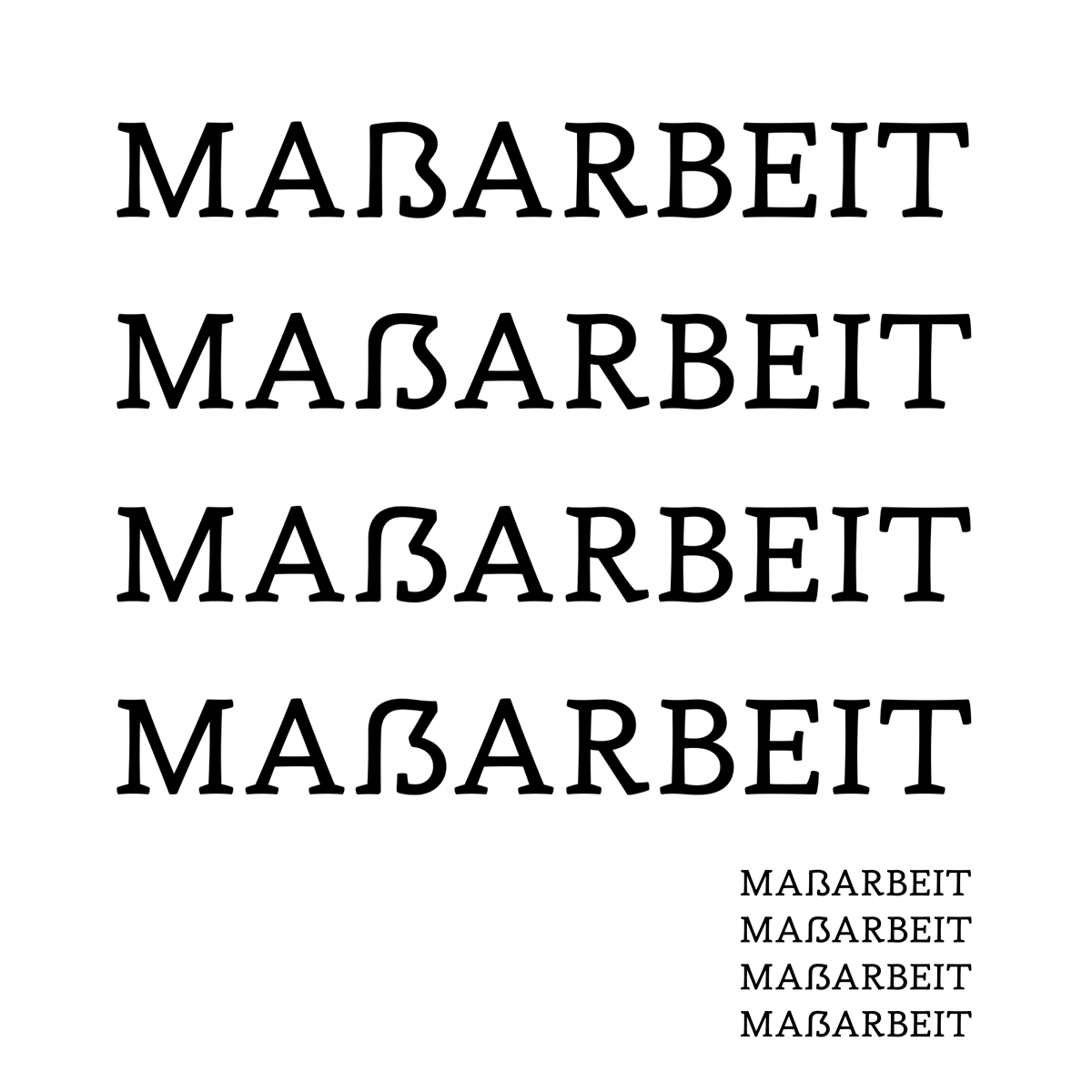
Keine Frage. Aber wir wissen ja aus Erfahrung was passiert, sobald die Debatte um alte und neue Rechtschreibung wieder entflammt. Und in Pachulkes sehe ich schon wieder die Funken sprühen. Aber das sollte dann an anderer Stelle diskutiert werden.
Solange es nur um historische Zusammenhänge des ß geht, ist ja alles in Ordnung.
Ich schließe nicht von meiner Eszett-Gewohntheit auf einen Mangel der SS-Schreibung, sondern von den Grundsätzen unserer Rechtschreibung. Das habe ich doch erklärt.
Genauso, wie ich doch schon erklärt habe, dass die Schreibung ‹ss› den Grundsätzen unserer Rechtschreibung sowieso nicht entspricht. Da nun aber bei der Schreibung ‹ss› die Grundsätze unserer Rechtschreibung gar nicht zum Zuge kommen, beruht dein Schluss eben doch auf deiner Eszett-Gewohnheit.
Willst Du abstreiten, daß Masse und Maße zwei unterschiedliche Wörter sind, die unterschiedlich ausgesprochen werden?
Das liegt mir fern. Was ich sage, ist bloss, dass keinerlei Mangel entsteht, nur wenn diese Unterscheidung nicht getroffen wird – genausowenig, wie wir irgendeinen Mangel erleiden, nur weil wir zwischen den unterschiedlichen und unterschiedlich ausgesprochenen Wörtern «umfahren» und «umfahren» nicht unterscheiden, oder «modern» und «modern», oder «Lache» und «Lache» oder «raste» und «raste» u.v.a.m.
Die Möglichkeit zur Unterscheidung nicht zu haben, ist für meine Begriffe ein Mangel.
Selbstverständlich, und zwar einfach deshalb, weil du es dir so gewöhnt bist. Wenn du es dir anders gewöhnt wärst, dann empfändest du jedoch keinerlei Mangel. In der Schweiz sind wir es uns anders gewöhnt, so dass die Schweizer Schreibung auf keinen Fall als mangelhaft erscheint. Es ist also nur eine Frage der Gewohnheit, und nicht eine Frage der Mangelhaftigkeit. Wenn du das nicht einsiehst, so liegt das wohl daran, dass du nicht von deiner eigenen Gewohnheit abstrahieren willst.
Wir können Verschiedenes unter einer mangelhaften Schreibung verstehen:
• Eine Schreibung ist mangelhaft, die unserer Gewohnheit nicht entspricht. In diesem Sinn ist immer die jeweils andere Schreibung mangelhaft. Es ist also ein durchaus nutzloser Begriff von Mangelhaftigkeit.
• Eine Schreibung ist mangelhaft, wo zwei unterschiedlich ausgesprochene Wörter nicht unterschieden werden. In diesem Sinn ist die deutsche Rechtschreibung grundsätzlich mangelhaft und – zugegeben – die Schreibung ohne ‹ß› ein wenig mangelhafter als die Schreibung mit ‹ß›, was jedoch angesichts der Vielzahl von weiteren nicht unterschiedenen Wörtern kaum ins Gewicht fällt.
• Eine Schreibung ist mangelhaft, bei der grundsätzliche praktische Probleme entstehen, so dass die Funktion der Schrift als Kommunikationsmittel beeinträchtig wird. In diesem Sinn ist selbstverständlich weder die Schreibung mit ‹ß› noch die Schreibung ohne ‹ß› mangelhaft, denn beide erfüllen problemlos alle praktischen Anforderungen.
• Eine Schreibung ist mangelhaft, die handfeste praktische Probleme verursacht, etwa in Schriftgestaltung oder Didaktik. In diesem Sinn ist die deutsche Rechtschreibung grundsätzlich mangelhaft und die Schreibung mit ‹ß› ein wenig mangelhafter als die Schreibung ohne ‹ß› – etwa weil sie, um mal wieder zum Thema des Threads etwas beizutragen, komplizierte Probleme im Versalsatz verursachen kann (von der einfachen Lösung, dass das ‹ẞ› ein gewöhnlicher Grossbuchstabe wäre, sind wir weit entfernt) –, was jedoch angesichts weiterer Probleme wie der grossen Umlautbuchstaben oder der Massierung von Grossbuchstaben kaum ins Gewicht fällt.
Ralf: Kannst Du bitte die betreffenden Beiträge in einen neuen Strang, bspw. mit dem Titel „Ist es ein Mangel, statt ‚ß‘ ‚ss‘ zu schreiben?“, verschieben?
Genauso, wie ich doch schon erklärt habe, dass die Schreibung ‹ss› den Grundsätzen unserer Rechtschreibung sowieso nicht entspricht. Da nun aber bei der Schreibung ‹ss› die Grundsätze unserer Rechtschreibung gar nicht zum Zuge kommen, beruht dein Schluss eben doch auf deiner Eszett-Gewohnheit.
Die Tatsache, daß das s gewisse Besonderheiten hat, heißt nicht, daß für das s überhaupt keine der gewöhnlichen Grundsätze unserer Rechtschreibung gelten. Das ist ein völlig haltloser Schluß. Doppelung des s bedeutet Kürzung, genauso wie bei jedem anderen Selbstlaut (Rose — Rösser), ganz unabhängig davon, ob es in dem Beispiel noch weitere Besonderheiten beim s gibt.
Die ß-Schreibung ist eingeführt und funktioniert gut. Ich sehe nur Nachteile darin, sie abzuschaffen, weil sie eine sonst nicht mögliche Unterscheidung ermöglicht. Genauso wie ich beispielsweise die Unterscheidung von u und v sinnvoll finde und nicht missen möchte. Da diese Unterscheidungsmöglichkeiten von vielen Menschen als sinnvoll angesehen werden, ist es ein Mangel, sie nicht zu haben. Nur weil Du eine solche Unterscheidung nicht als nötig empfindest, heißt das nicht, daß diese Unterscheidung sinnlos ist. Nur weil Du etwas nicht als mangelhaft empfindest, heißt das nicht, daß es nicht mangelhaft ist.
Bitte verstehe „mangelhaft“, wenn ich es sage, nur in dem Sinne: etwas Sinnvolles fehlt. Und jetzt behaupte bitte nicht, das ß sei sinnlos. Es hat einen Sinn, weil es nach bestimmten Regeln angewandt wird und deshalb auch eine Bedeutung trägt. Deshalb bin ich für das Eszett, nicht weil ich daran gewöhnt bin.
bin wieder mal an der Canapé dran, und da am Finale zum Versal-ß.
Es sind 4 Varianten verblieben, wobei ich die erste fast ausschließen will (zu minuskelartig, zu weit weg vom sich etablierenden Aufbau).
Bei den anderen 3 bin ich mir aber nicht sicher, was meint ihr?
Ich finde 2 ja auch nicht schlecht, 4 ist aber meiner persönlichen Meinung nach sowohl in der großen als in der kleinen Schriftgröße am eindeutigsten.